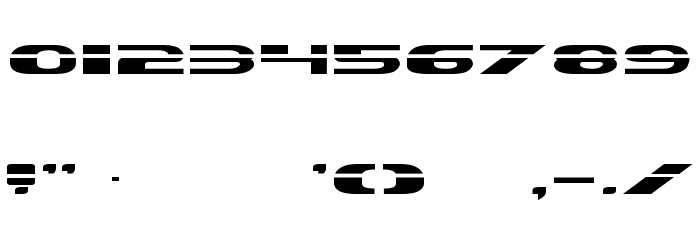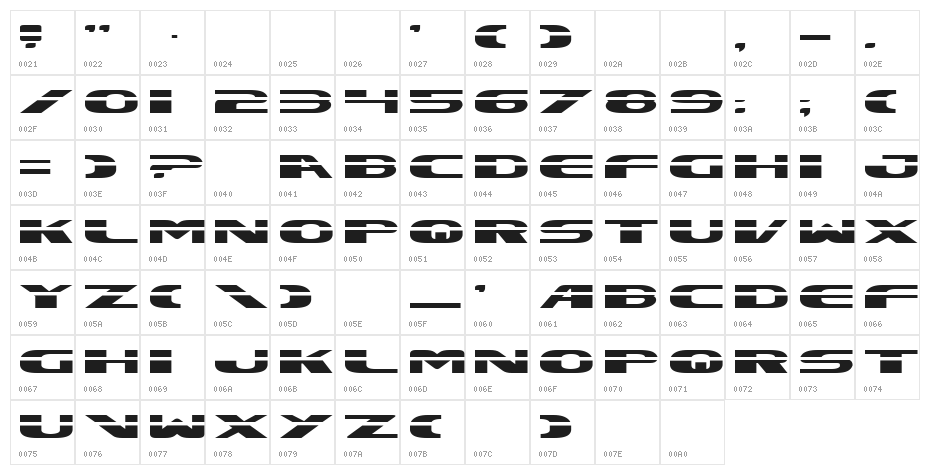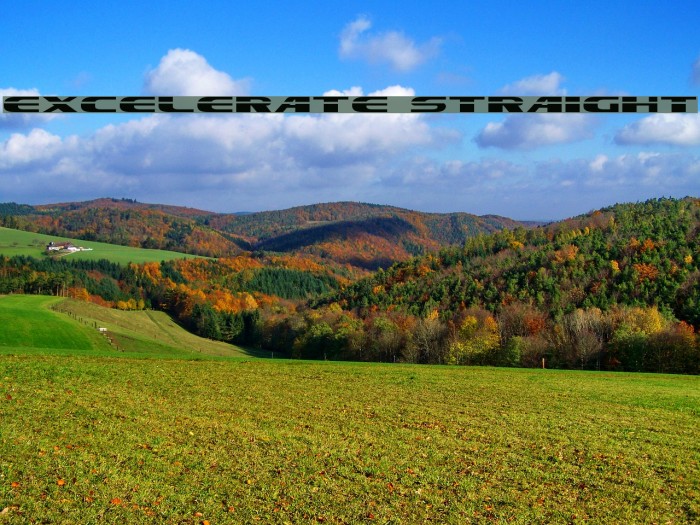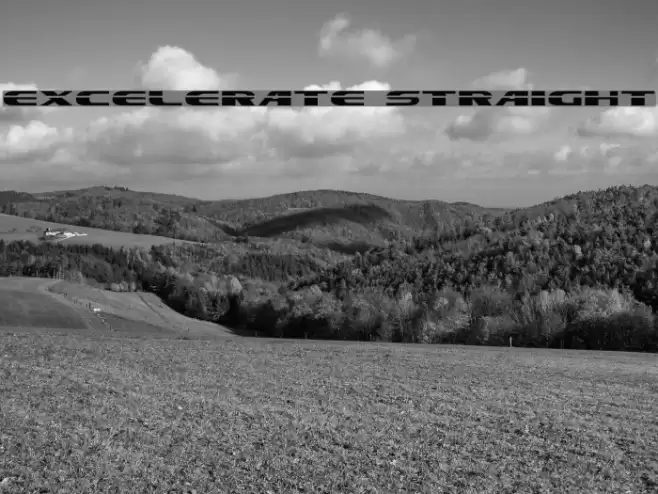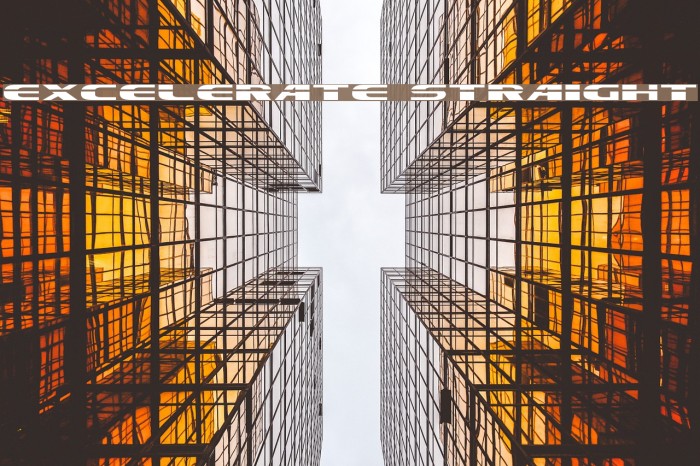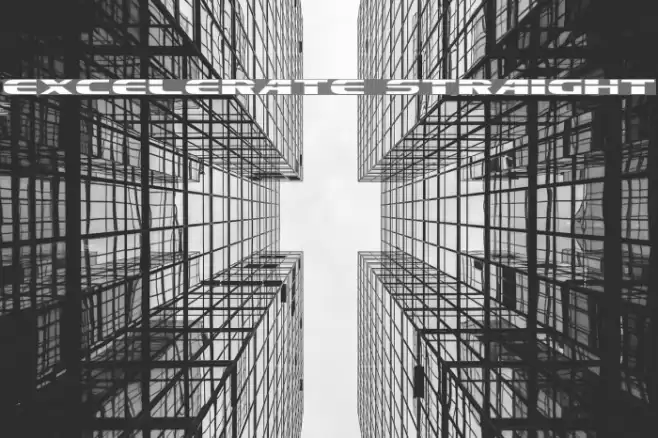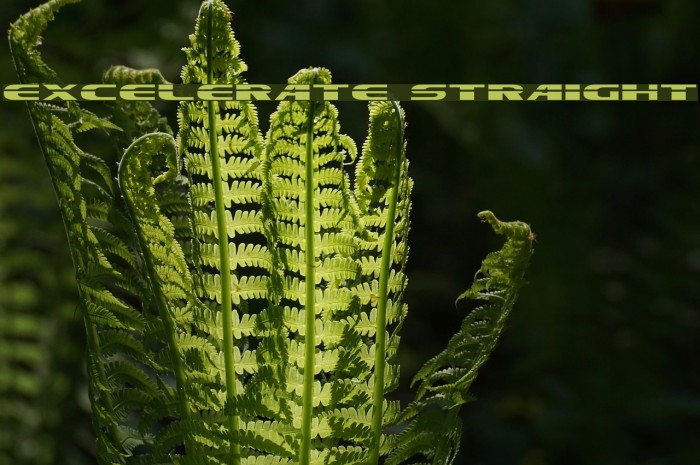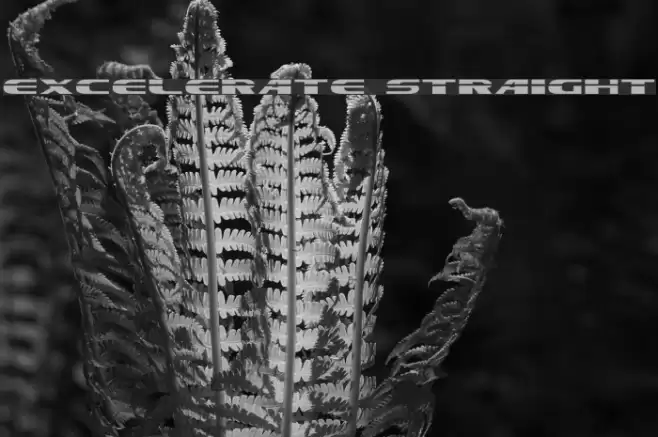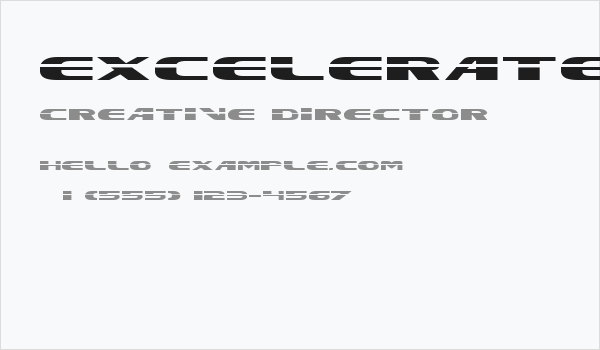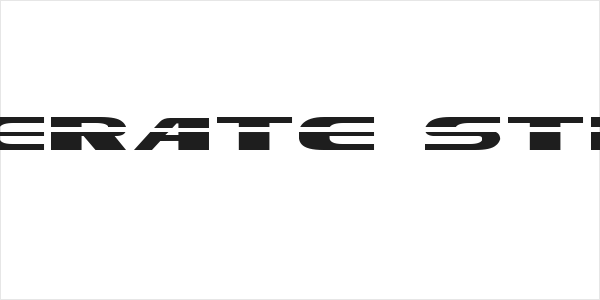
Excelerate Straight Font
| 名前 | Excelerate Straight |
| ウェイト | Expanded |
| カテゴリ | Capitals |
| おすすめプロジェクト | Ideal for tech branding, futuristic posters, video game titles, and sci-fi themed projects. |